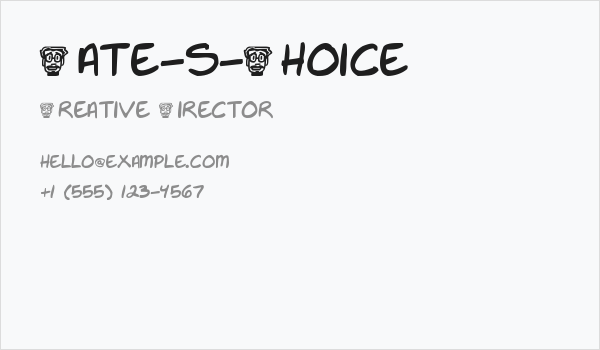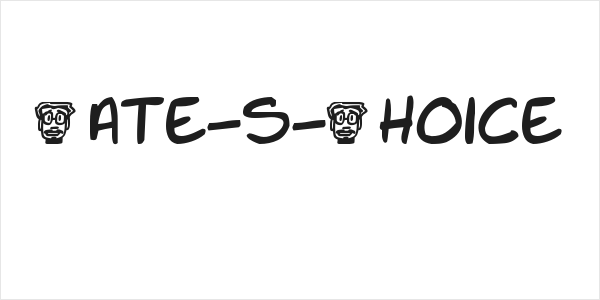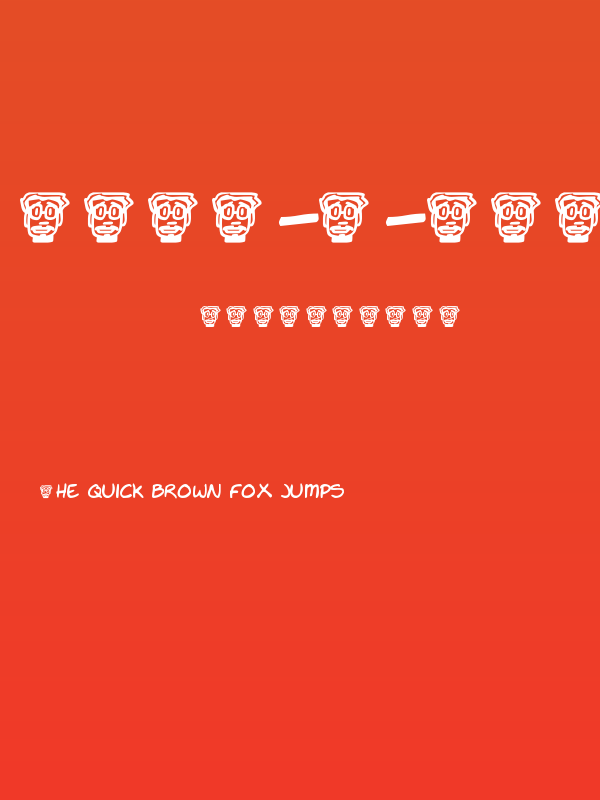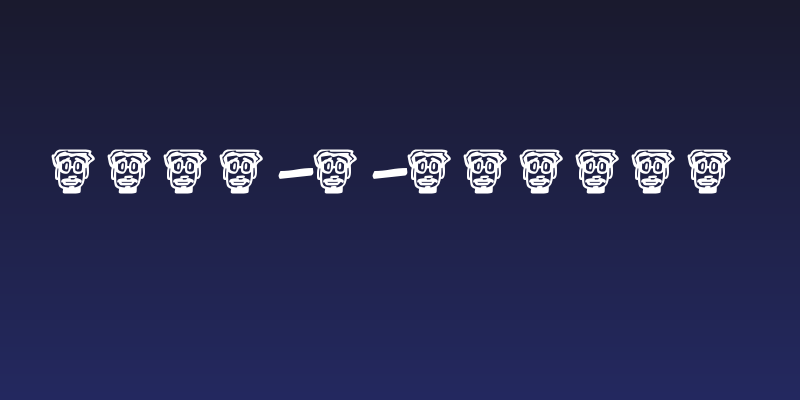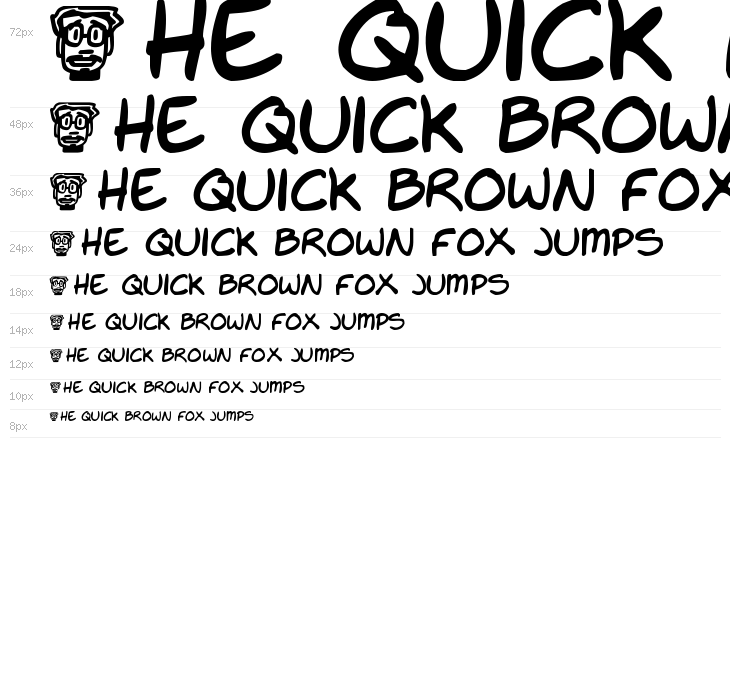
Nate-s-Choice Font
✎ Comic
| Gesamtstil | Playful, Casual |
| Vorgeschlagene Projekte | Ideal for children's books, comic strips, playful branding, and creative posters. |